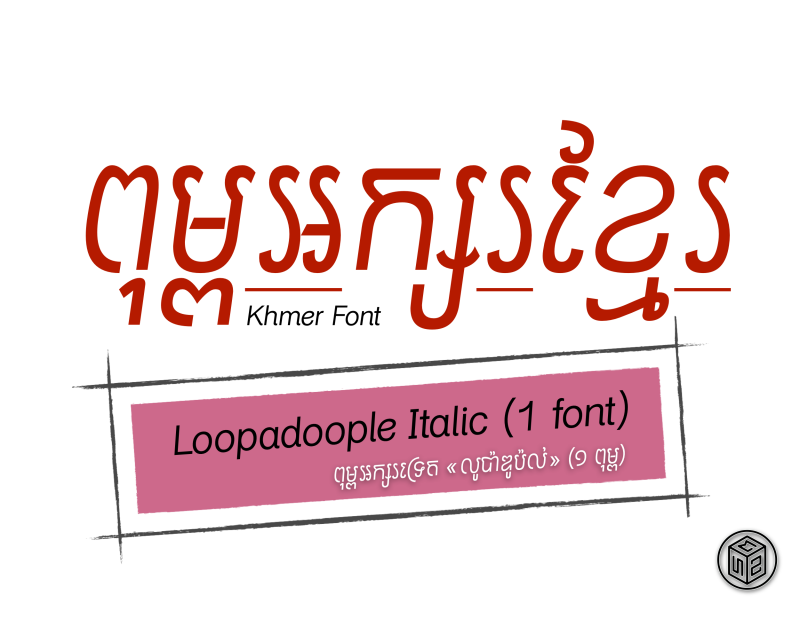
Loopadoople Hairy [Single] Italic (1 font)
Single download file of the classic serif style Khmer font - Loopadoople Hairy Italic
Loopadoople គឺជាពុម្ពអក្សរខ្មែរ Opentype ដែលត្រូវបានរចនាឡើងជាពិសេសឱ្យប្រើការក្នុងស្លាកផលិតផលសម្រាប់បង្កើនយីហោទំនើប។ ក្នុងកំណែកញ្ចប់ «សក់» ទម្រង់អក្សរនៃពុម្ពអក្សរនេះគឺស្រដៀងនឹងអក្សរខ្មែរដែលមានសក់ពីលើតួនីមួយៗដដែល ដែលផ្តល់នូវការអានអត្ថបទវែងដ៏ភាពងាយស្រួល។
Loopadoople is an Opentype Khmer font that was designed specifically for product labels to enhance modern branding. In the Hairy version, the letterforms of this font is similar to the Khmer script with hair on top of each character, which provides easy reading of long texts.